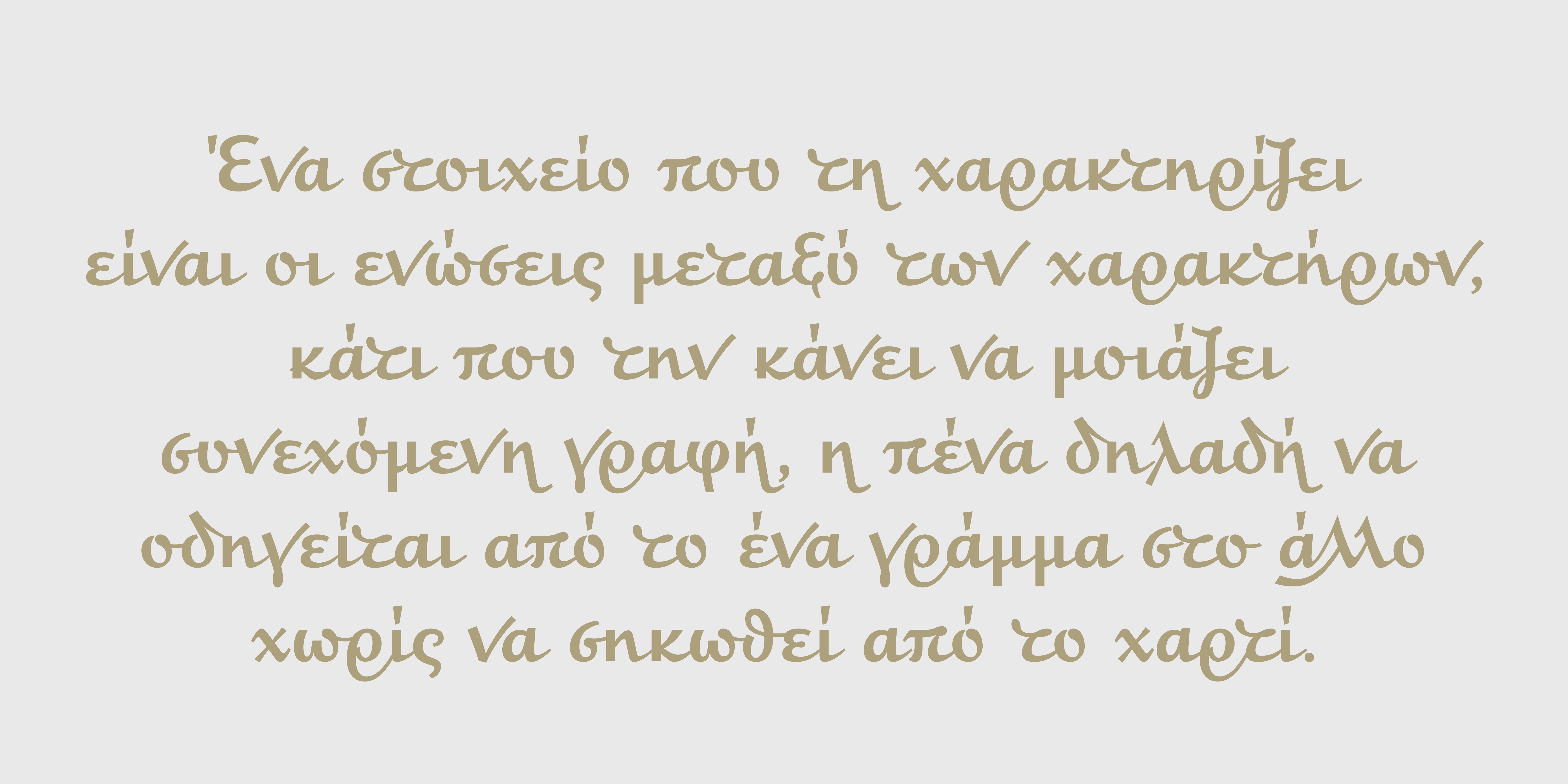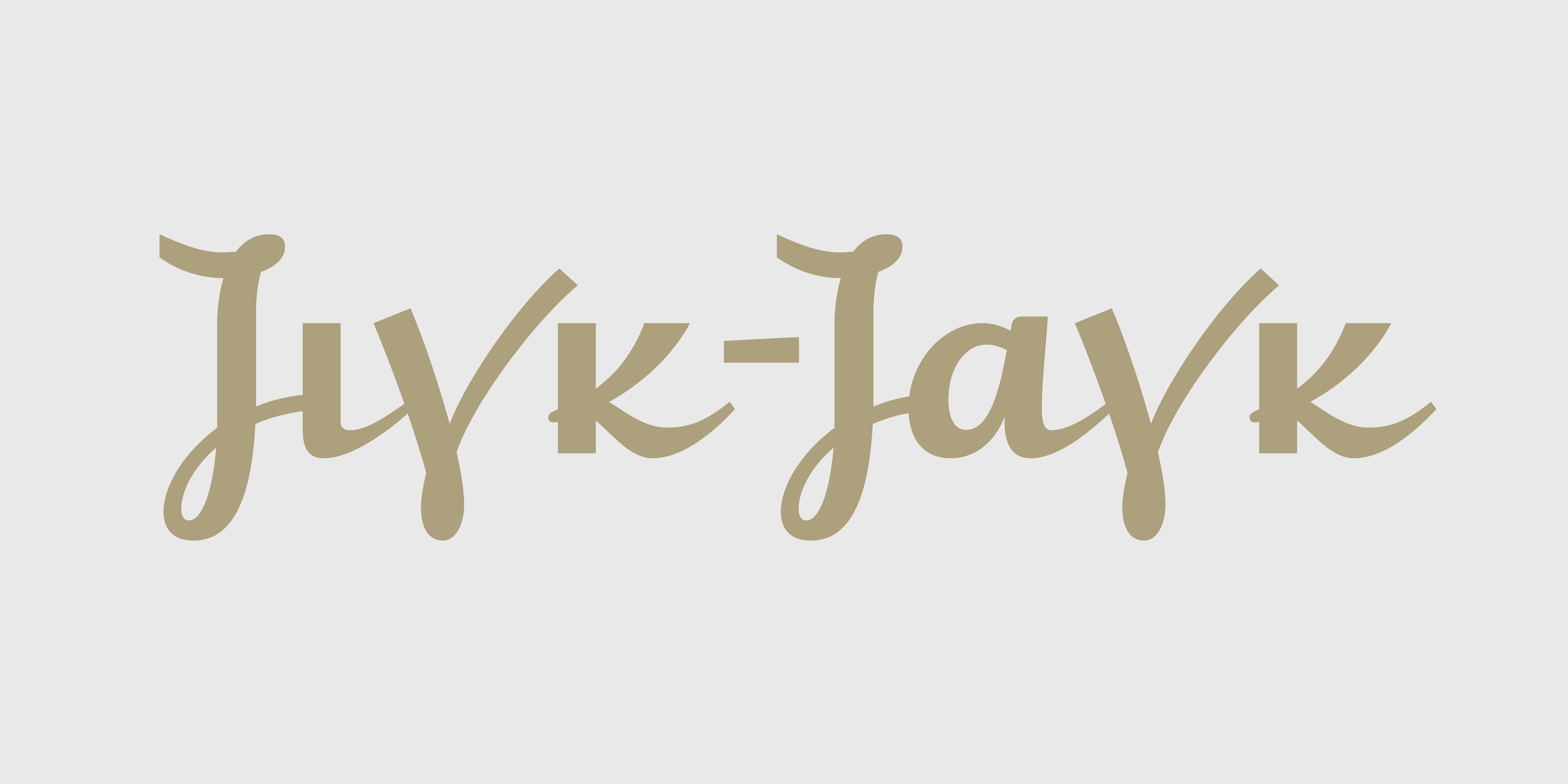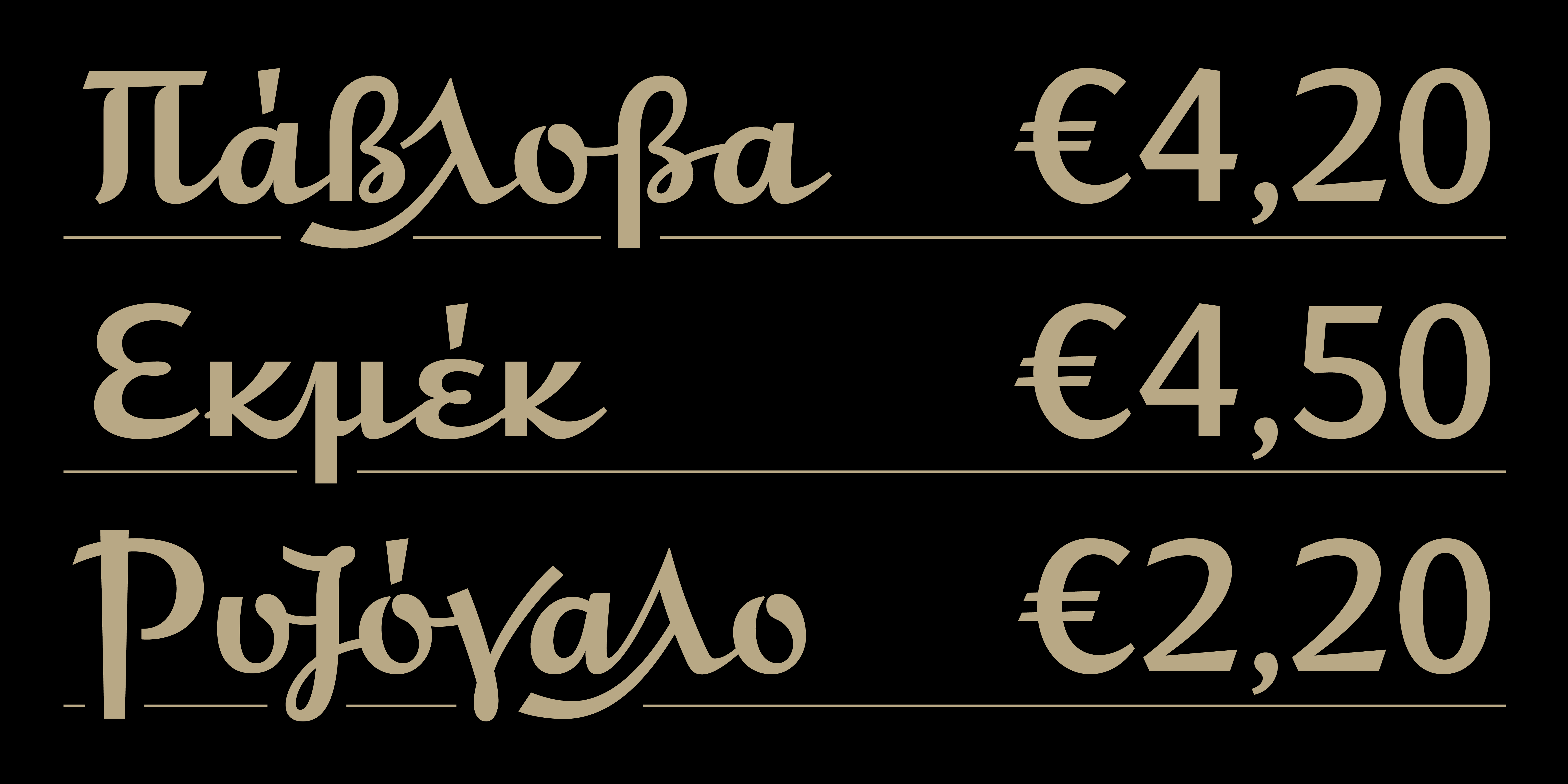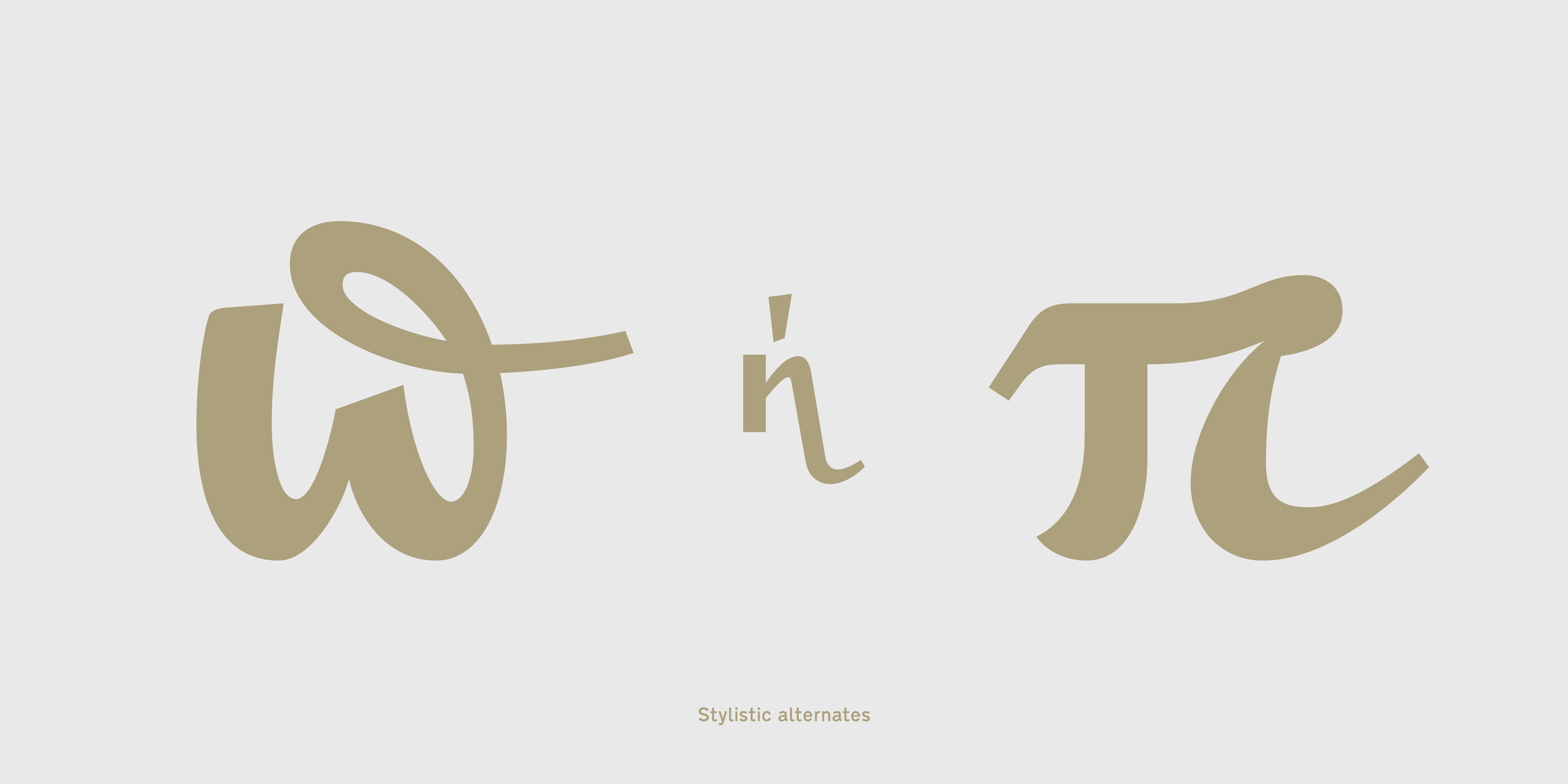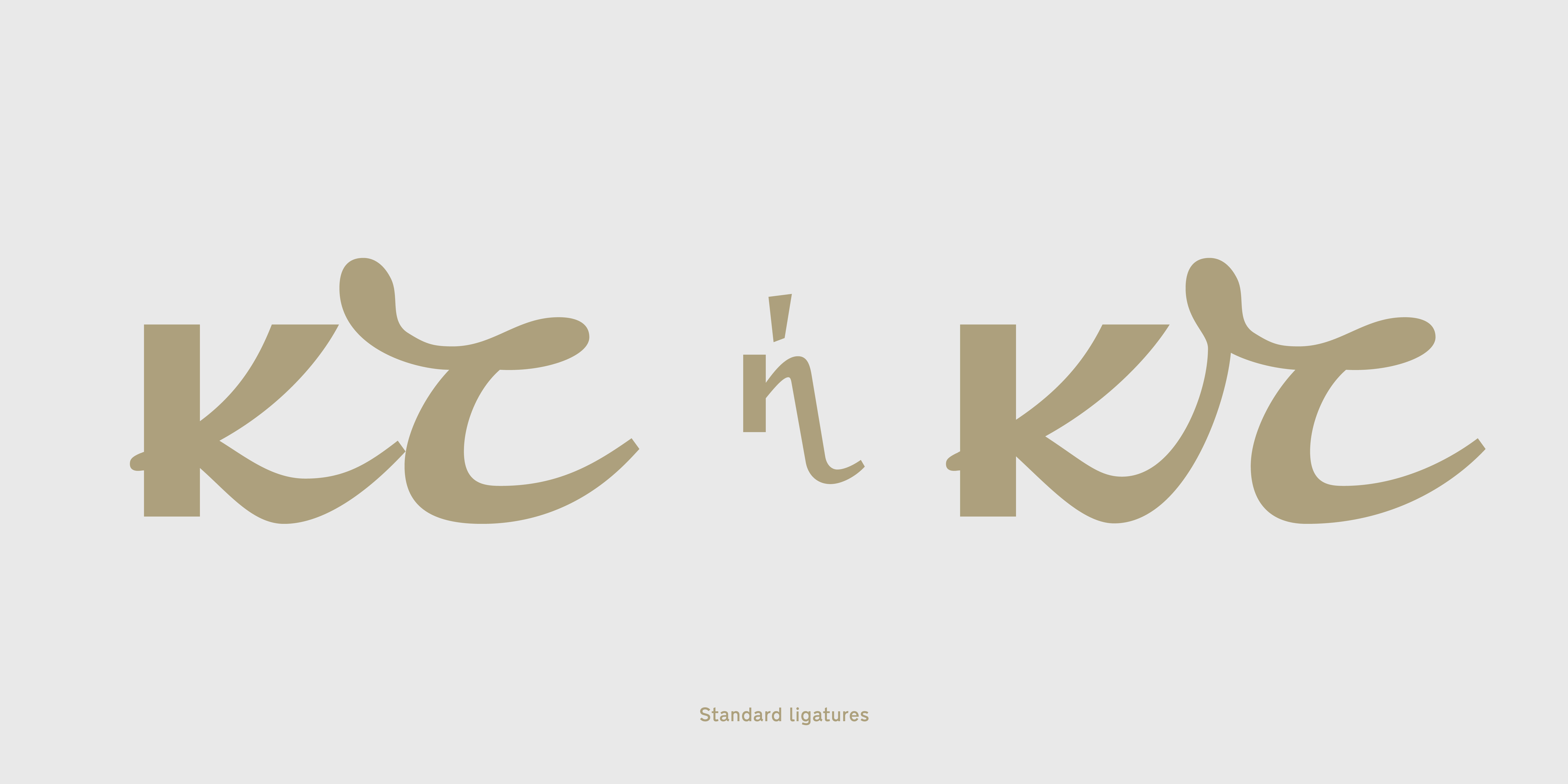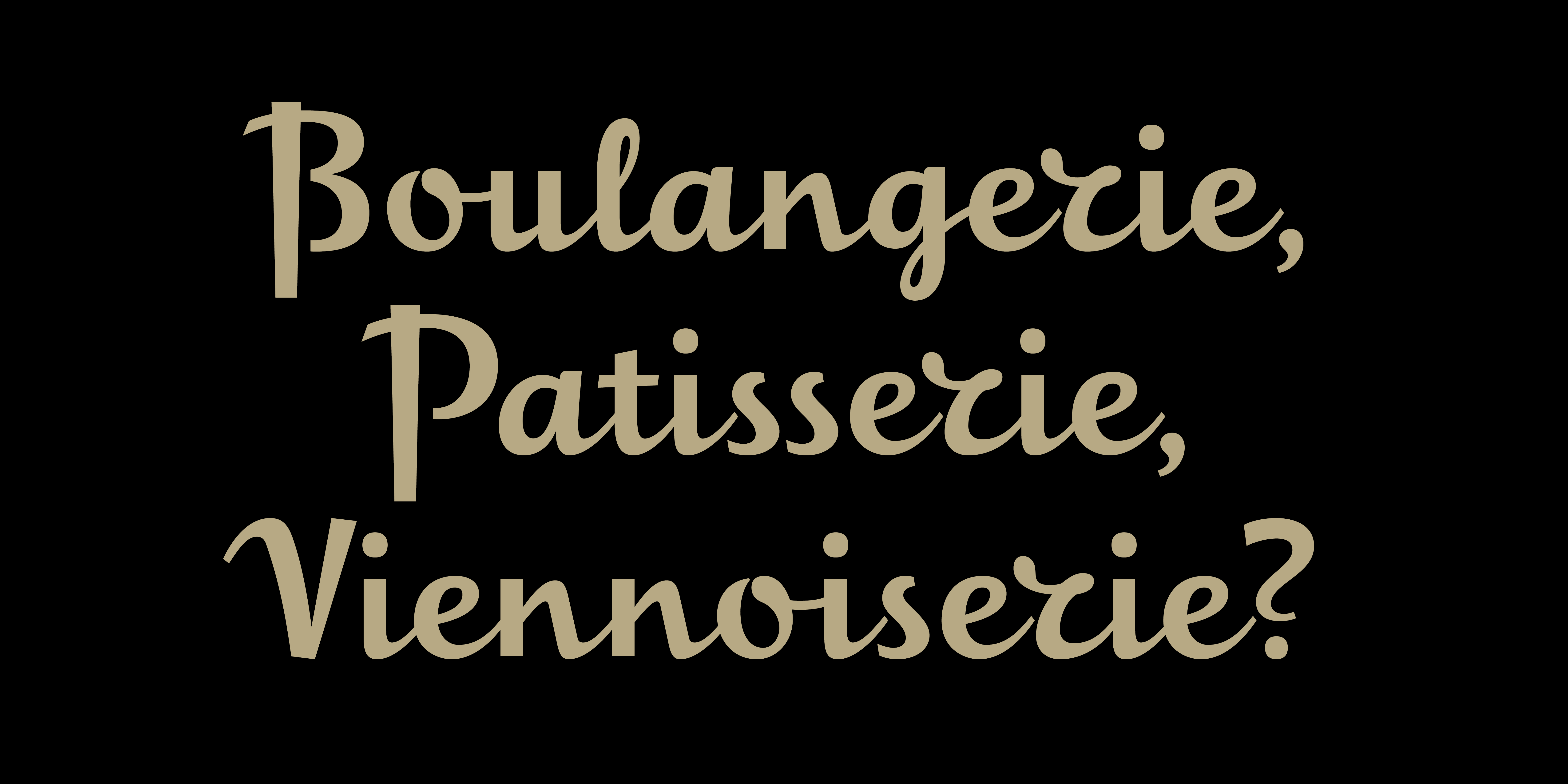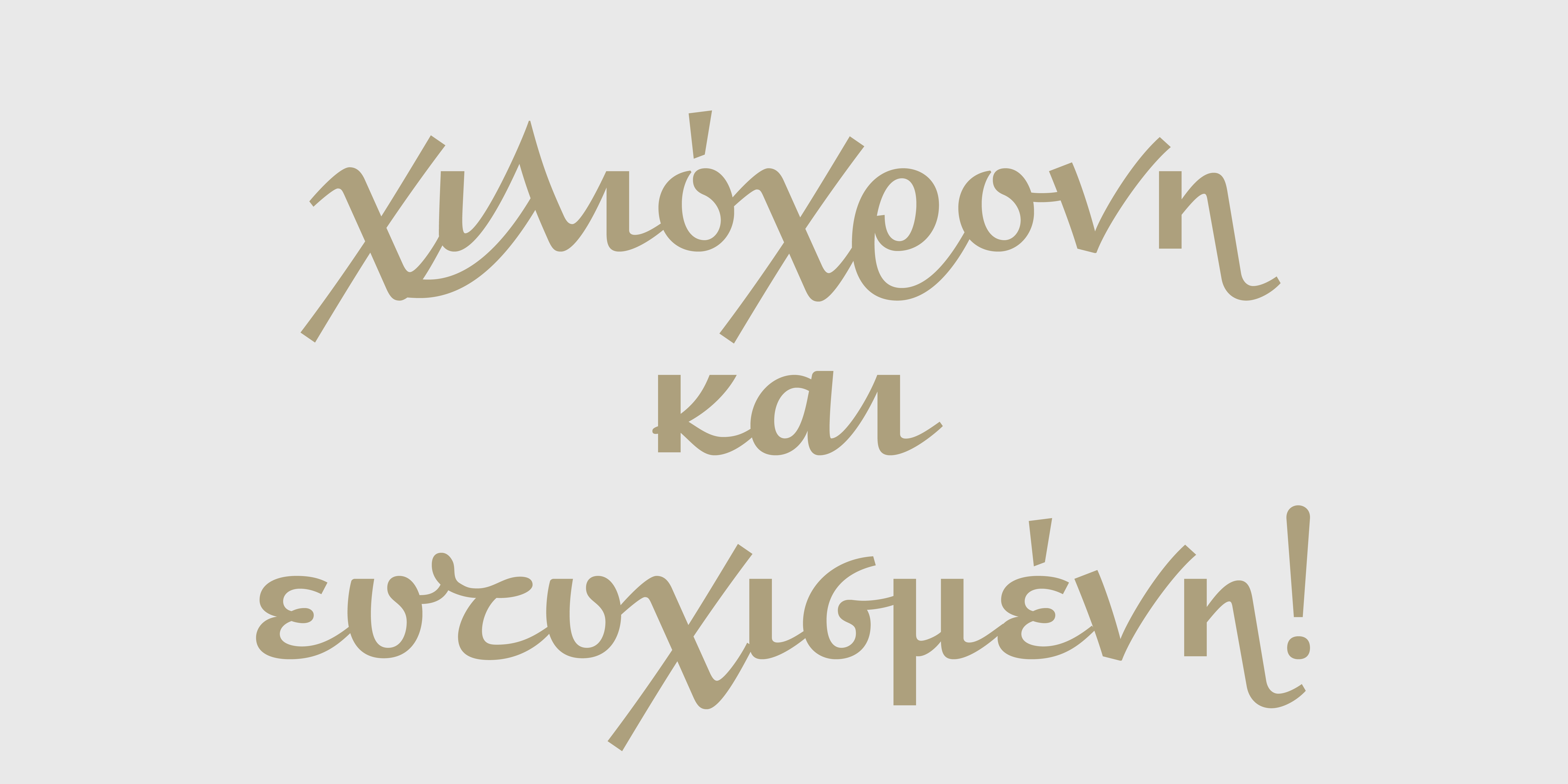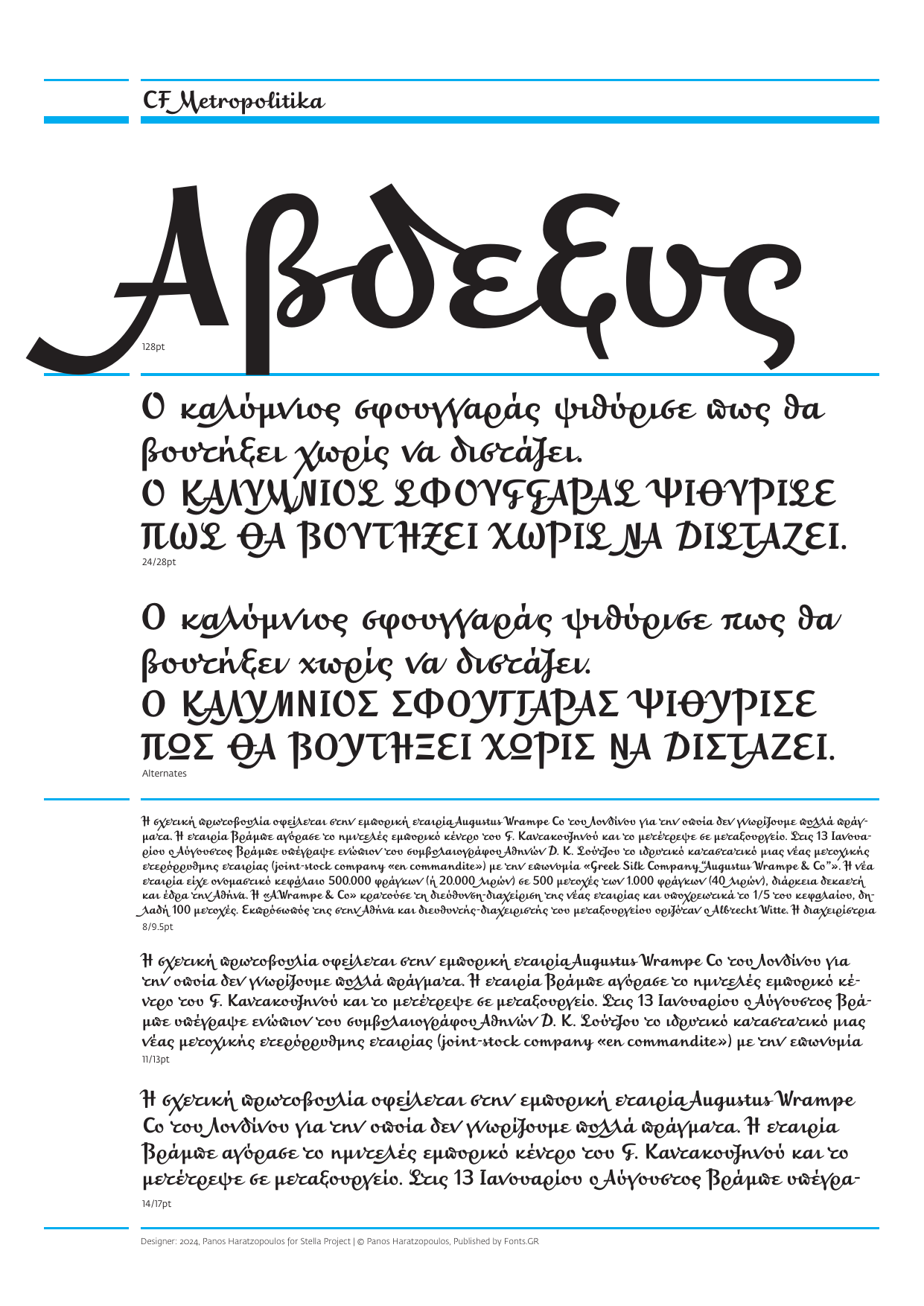
Metropolitika
Η CF Metropolitika είναι μια ιδιαίτερη γραμματοσειρά του Στέλλα Πρότζεκτ. Το χαρακτηριστικό της είναι πως πρόκειται για μια όρθια —και όχι επικληνή— χειρόγραφη γραμματοσειρά, κάτι αρκετά σπάνιο μεταξύ του αρχειακού υλικού που μελετήθηκε. Στον πυρήνα της βρίσκεται η επιγραφή του γνωστού ζαχαροπλαστείου «Μητροπολιτικόν» στο κέντρο της Αθήνας, όπου πρόκειται για μια όρθια χειρόγραφη γραμματοσειρά, ιδιαίτερα εκφραστική, με πολύ καλλιγραφική αίσθηση και ενώσεις μεταξύ των χαρακτήρων. Με ελάχιστα άλλα αντίστοιχα παραδείγματα γραφής, η γραμματοσειρά «εφευρέθηκε» αφού επιχειρήθηκε να ανασυσταθούν όλοι οι χαρακτήρες που περιλαμβάνει με βάση αυτήν την επιγραφή. Ένα άλλο στοιχείο που τη χαρακτηρίζει είναι οι ενώσεις μεταξύ των χαρακτήρων, κάτι που την κάνει να μοιάζει συνεχόμενη γραφή, η πένα δηλαδή να οδηγείται από το ένα γράμμα στο άλλο χωρίς να σηκωθεί από το χαρτί. Για να επιτευχθεί αυτό χρειάστηκε να σχεδιαστούν εκατοντάδες εναλλακτικοί χαρακτήρες και συμπλέγματα από τα οποία επιλέγονται αυτόματα τα κατάλληλα κατά την πληκτρολόγηση.